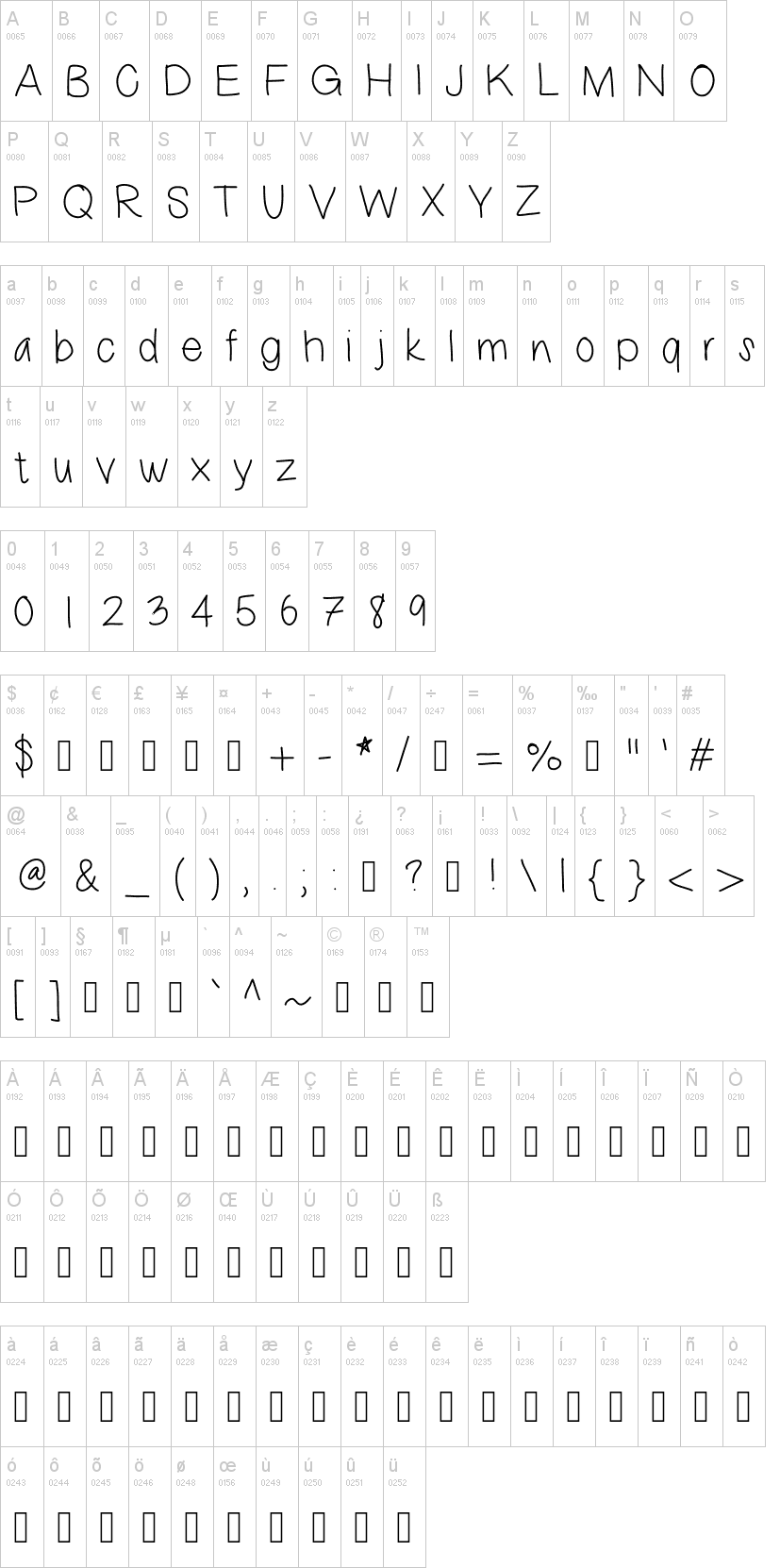
This Sux
This Sux 是一款比较有趣的手写字体,它的特点是粗犷、活泼、娇小,给人一种混乱、随意、放肆的感觉。这款字体的字形可以让你的文字更加有趣,它的笔触流畅,可以让你的文字更加生动。它的字体设计简单,可以让你的文字更加精致。它的特点是灵活的笔触,可以让你的文字更加有趣。
This Sux是一款非常不错的手写艺术字体,具有很好的视觉感,适合于文化类的宣传设计、商业类品牌的广告和产品包装设计以及个性化文字排版等较多场景。
This Sux字符映射图